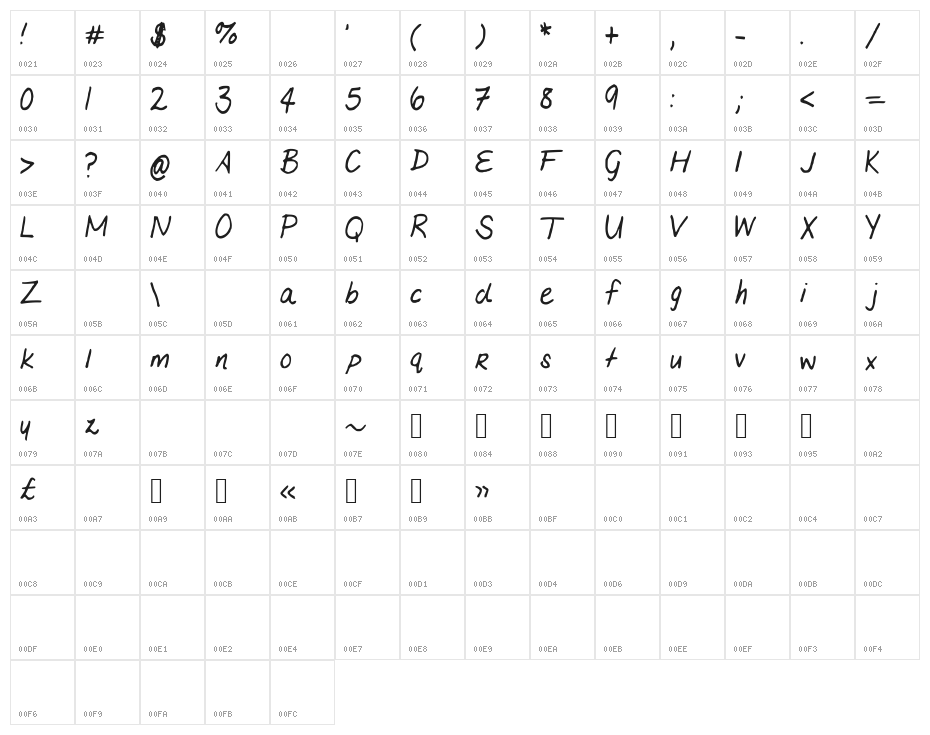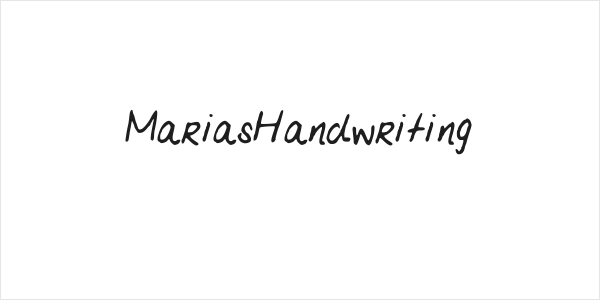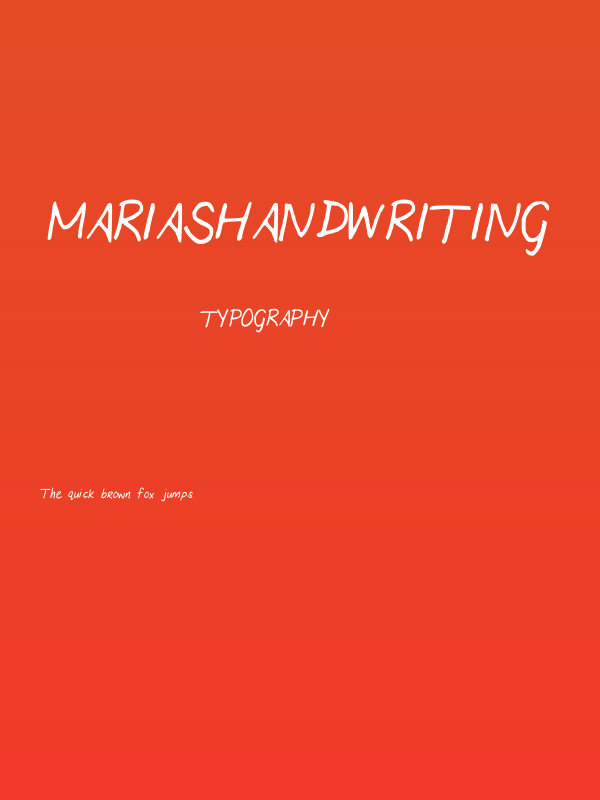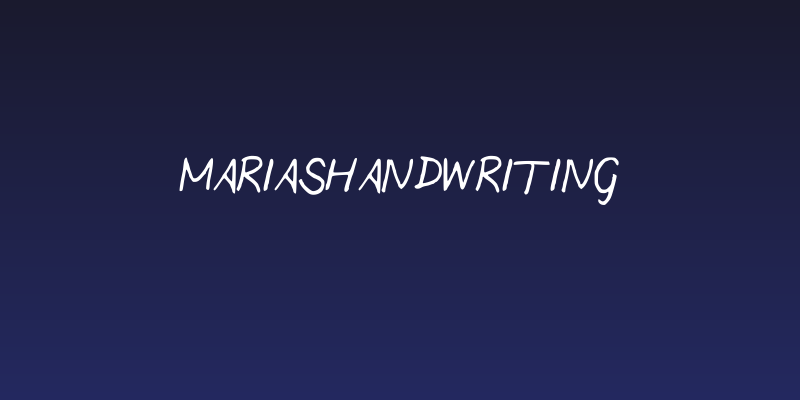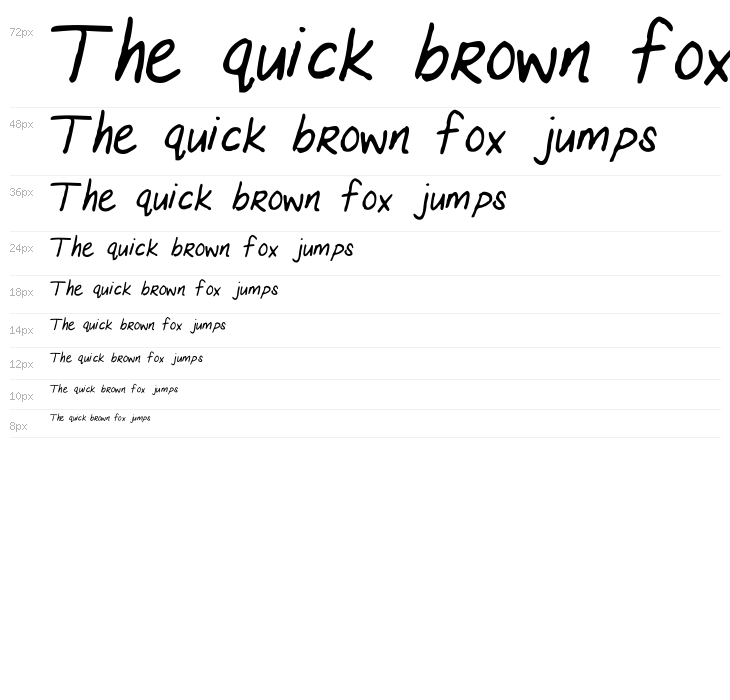
MariasHandwriting Font
| Stile generale | Casual, Personal |
| Caso d'uso | Invitations, Greeting cards, Personal notes |
| Progetti proposti | Ideal for personal notes, invitations, greeting cards, and any project requiring a personal, informal touch. |